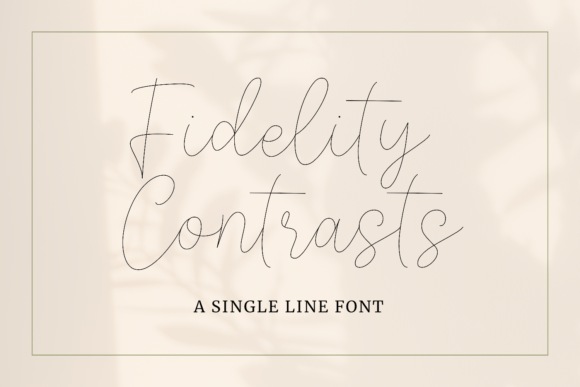
Fidelity Contrasts
Созданный с высокой точностью, Fidelity Contrasts предоставляет чистые векторы, плавную типографику и коммерческую лицензию для вашего спокойствия.